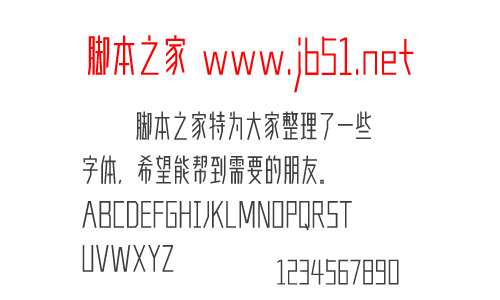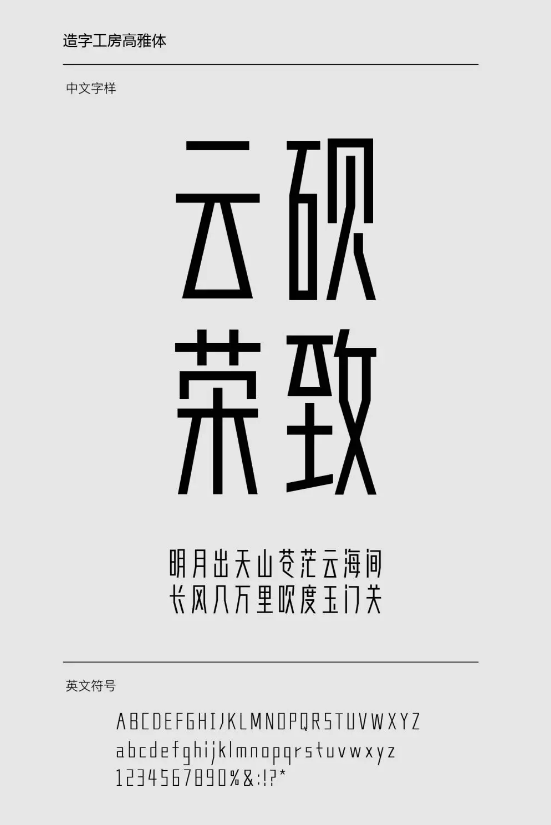
造字工房高雅體字形秀麗修長,端秀清新,姿態(tài)研美端莊,盡顯知性優(yōu)雅之美感。筆畫整齊平正,結(jié)構(gòu)簡遠平和,中宮自然舒適,架構(gòu)層次分明,留白均勻,氣韻流暢,簡約又極富現(xiàn)代氣息。適用于大標題及個性品牌設(shè)計推廣等環(huán)境。歡迎喜歡造字工房高雅體的朋友前來下載使用。